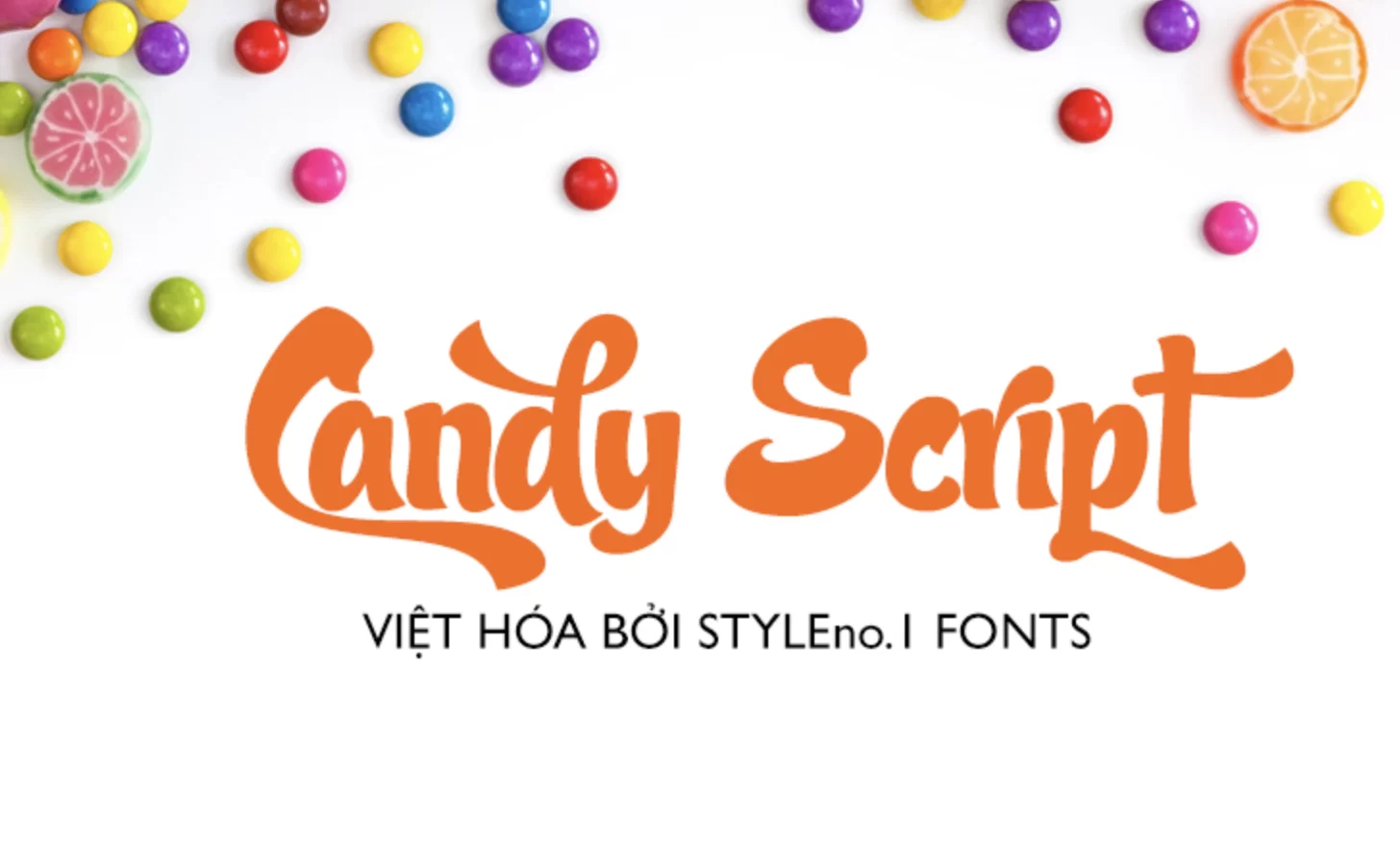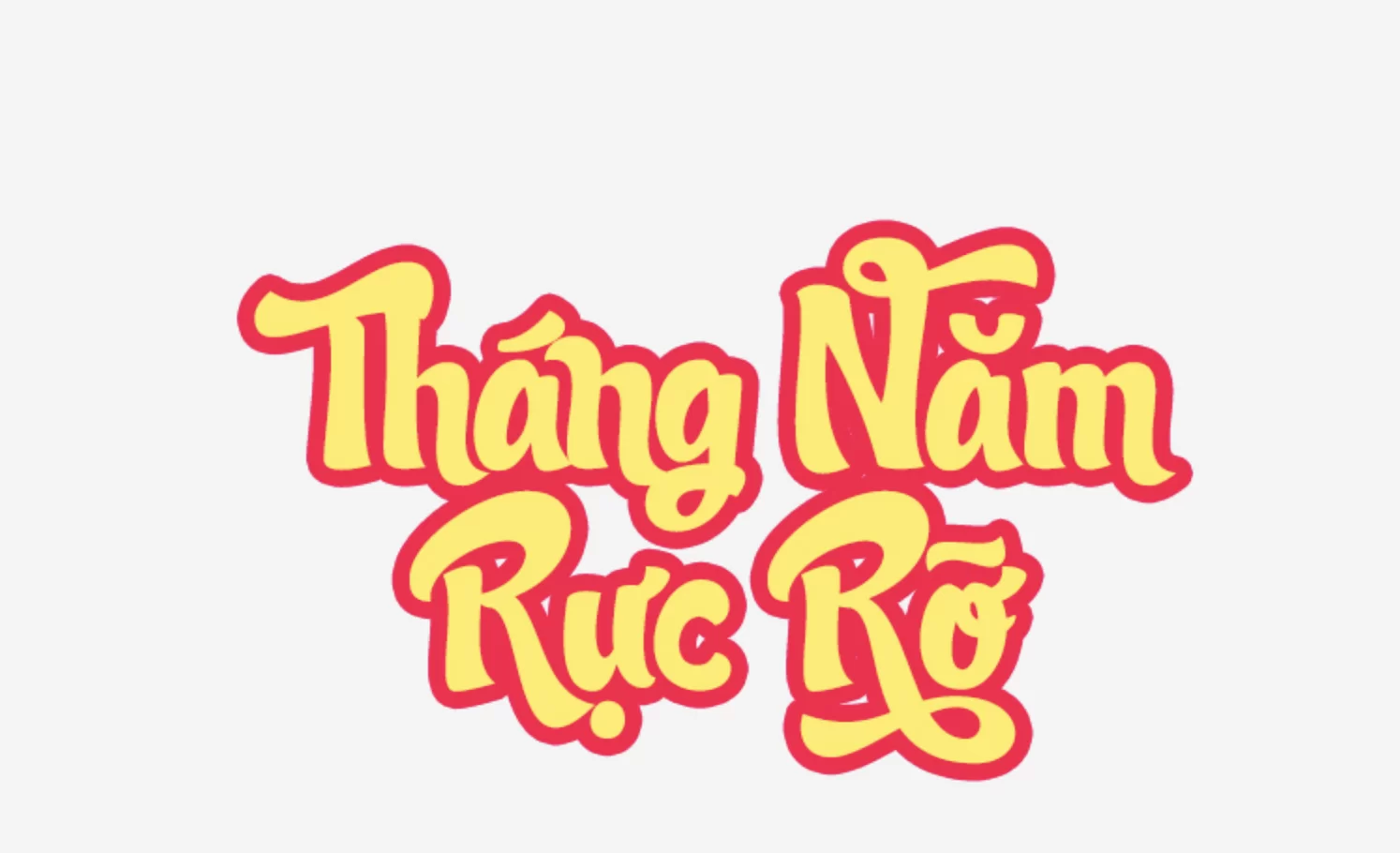
Lấy cảm hứng từ văn hóa của Argentina, Candy Script là một Font chữ đậm xen kẽ với hầu hết các chữ hoa và chữ thường, đều có cá tính riêng. OpenType có thể thay thế, hơn 600 ký tự.
Nhà thiết kế: Alejandro Paul
Font có hỗ trợ nhiều kiểu ký tự thay thế.